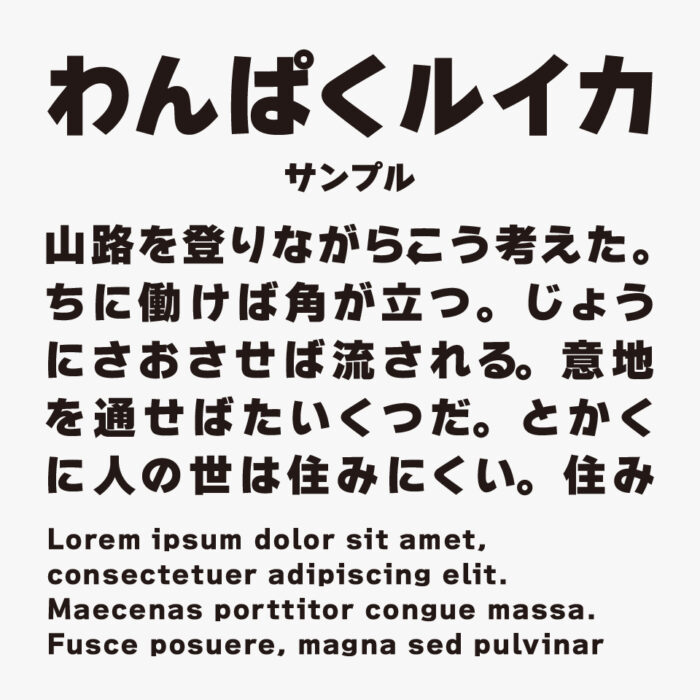
わんぱくルイカ
わんぱくルイカフォントは、ずっしりとした太さと丸みのある骨格が印象的な、元気いっぱいのゴシック体フォントです。
元気いっぱいでどこか愛嬌のある雰囲気があり、くっきりした親しみやすい「かな文字」、落ちついた雰囲気のある「漢字」とのバランスが良く、どんな場面でも使いやすいフォントです。
わんぱくルイカ